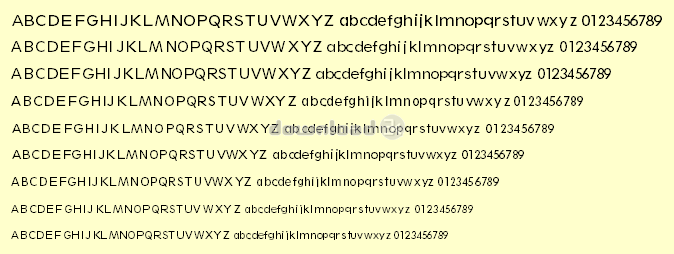
"Geometrische serifenlose Schrift"
Rubicon Sharpe Geordnet Schriftarten. Postscript. Geometrische serifenlose Schrift mit einem robusten Griff. Wie Spartan eingestuft. Für Zeitungs-Kleinanzeigen. Empfohlene Größe 5,5 Punkte. Präzise und deutete an, passender Font-Metriken, Standard-Zeichensatz, Kerning-Paare. Professionelle Druckqualität für Inkjet, Laser, Schriftsetzer zu 3500 dpi. Enthält 1-Studie Schriftart, senden Sie $ 12 bis 2-Produktion Schriften erhalten.Bedarf Older versions of Mac OS require Adobe Type Manager.